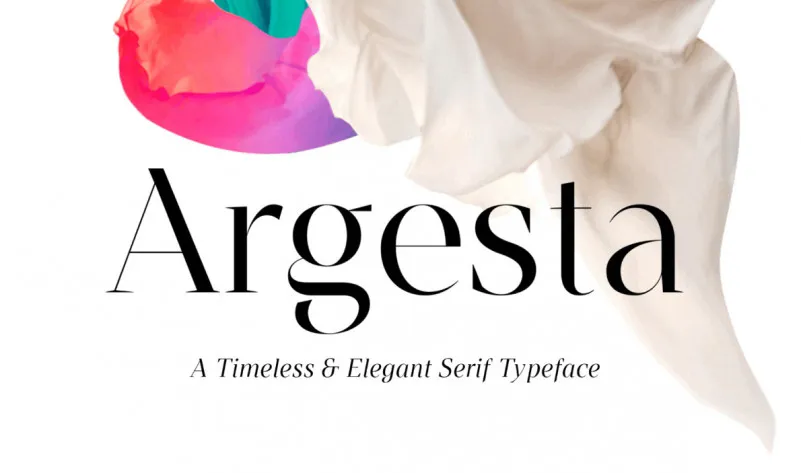
Argesta Font Family – Download Grátis
A Argesta Font Family é uma família moderna serif que oferece aos designers uma escolha elegante e sofisticada para projetos profissionais. Inspirado no estilo elegante de stencil serif, esta fonte combina a simplicidade clássica com características maduras, adequando-se perfeitamente para o estabelecimento de títulos poderosos e criações mais elaboradas. Ideal para quem busca dar um toque sofisticado em sua arte digital, essa família de fontes oferece 9 estilos variados, desde linhas finas até textos completos, incluindo itálicas verdadeiras que se ajustam perfeitamente às suas necessidades de design. Desenvolvida e compartilhada pela atipo®, a Argesta é uma opção ideal para quem busca um toque sofisticado em projetos gráficos ou digitais, combinando elegância com força visual.